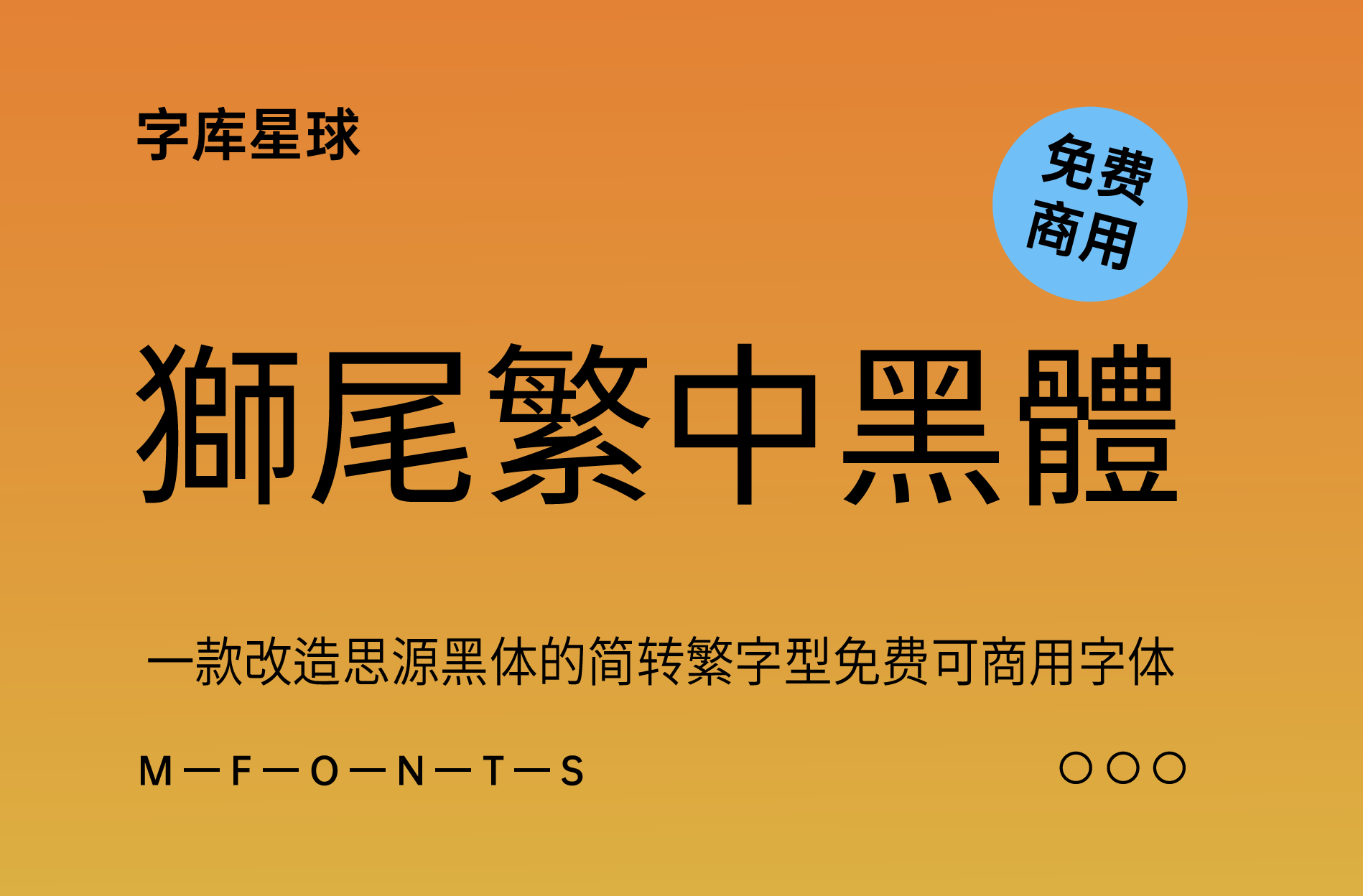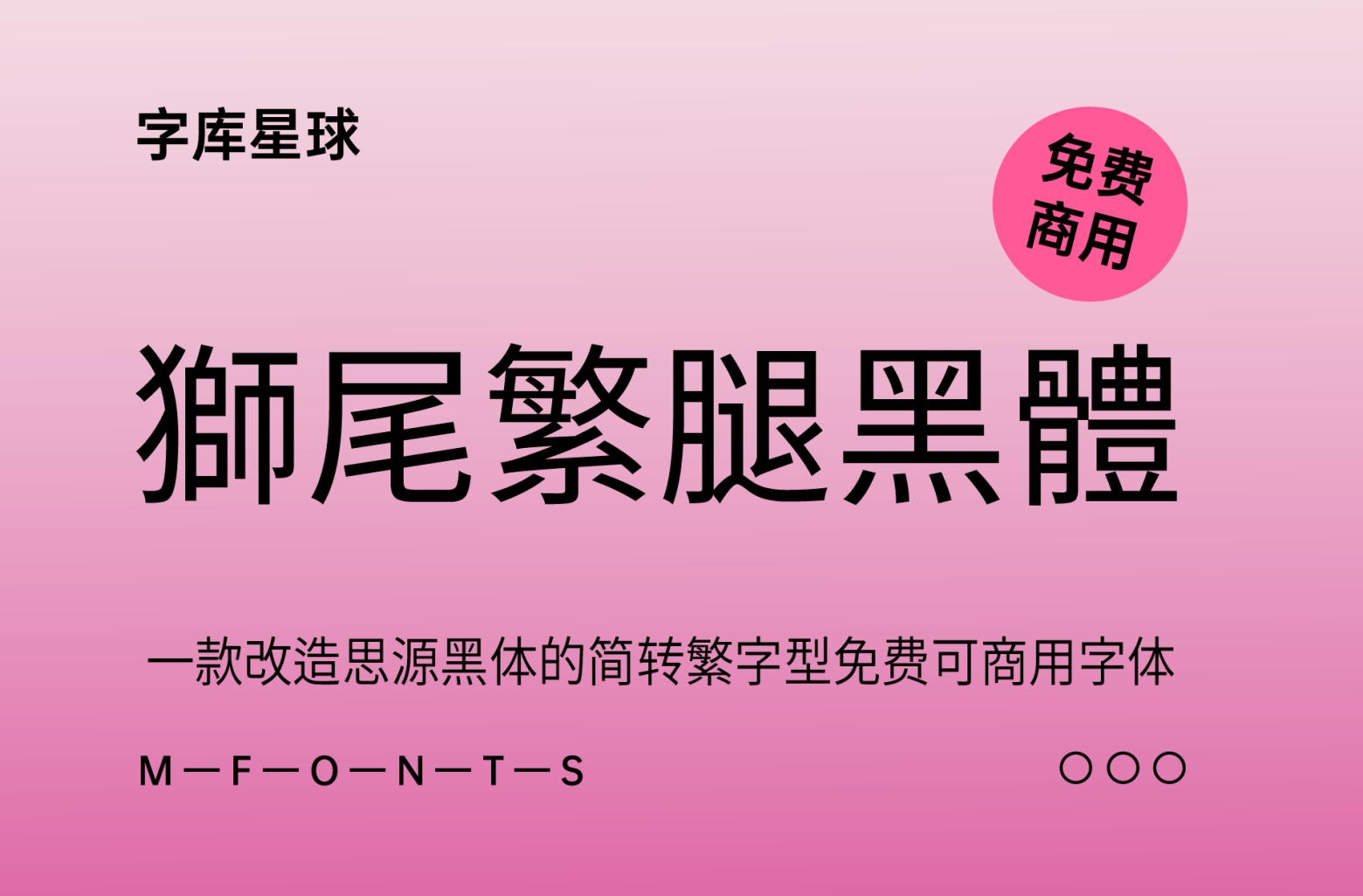
狮尾繁腿黑体基于思源黑体的简转繁字型;可以免费商用,欢迎大家自由应用、自由优化、自由改作!
狮尾繁腿黑体的特色是:简体字转成繁体字的字型档,没有很完美,比完全没转换好一点。不能处理「一简对多繁」,下列的简体中文会维持原样:「’干’,’了’,’卜’,’乃’,’才’,’亏’,’于’,’千’ ,”,’么’,’巨’,’丑’,’仇’,’云’,’扎’,’夭’,’凶’,’夫’,’斗’,’只’,’布’ ,’出’,’冬’,’发’,’它’,’他’,’占’,’扑’,’扣’,’托’,’奶’,’札’,’汇’,’吊’,’奸’,’夸’,’回’,’同’,’团’,’曲’,’伙’,’仿’,’后’,’朱’,’合’,’吃’ ,’匡’,’庄’,’村’,’志’,’里’,’别’,’谷’,’克’,’困’,’沉’,’佛’,’余’,’折’,’助’,’沄’,’芸’,’肖’,’坛’,’杆’,’表’,’杯’,’板’,’松’,’范’,’苎’ ,’刮’,’卷’,’弥’,’弦’,’舍’,’昆’,’岳’,’征’,’制’,’虮’,’杰’,’面’,’厘’,’咸’,’须’,’茧’,’药’,’荡’,’挂’,’挑’,’尝’,’秋’,’洒’,’适’,’洁’ ,’洼’,’荐’,’咱’,’炫’,’鸩’,’恹’,’钥’,’剃’,’咽’,’咯’,’背’,’炼’,’姜’,’拐’,’咨’,’恤’,’荫’,’昵’,’垒’,’党’,’获’,’借’,’脏’,’致’,’蚕’ ,’赶’,’家’,’晒’,’症’,’离’,’恶’,’娘’,’殷’,’栖’,’盏’,’绦’,”,’唉’ ,’席’,’捂’,’挽’,’效’,’核’,’栗’,’疱’,’瓶’,’疴’,’莼’,’浩’,’浚’,’涌’,’涂’,’凌’,’凄’,’准’,’烟’,’挨’,’焊’,’蝎’,’象’,’雇’,’游’,’剩’ ,’棹’,’搜’,’逾’,’愧’,’踊’,’演’,’历’,’升’,’划’,’向’,’冲’,’并’,’苏’,’系’,’你’,’刨’,’弄’,’泛’,’抵’,’呼’,’周’,’胡’,’炮’,’迹’,’宴’ ,’捆’,’崎’,’麻’,’棱’,’毁’,’暗’,’橹’,’台’,’局’,’采’,’复’,’蒙’,’雕’」由于无法处理,所以会直接略过。
「狮尾繁中黑体」与「狮尾繁腿黑体」差别在有没有拔脚,「拔脚」就是会有较少的笔画,例如移除「口」字的左右下角会多出的短线条。有拔脚的字会较圆,但是会造成有些字因直接去掉腿后左右不平衡、左右不对衬的「悬空」问题。改使用「腿」系列字体就不会有这个问题。
说明:由于“发”和“髮”在简中是同一个字“发”,目前不知如何处理一对多的对应,所以部份简体字还是维持原本的形态。
“狮尾繁腿黑体”设计上针对笔画粗细支援7种字重,所以不论大标、小标、简单的段落排版都能清晰辨识。